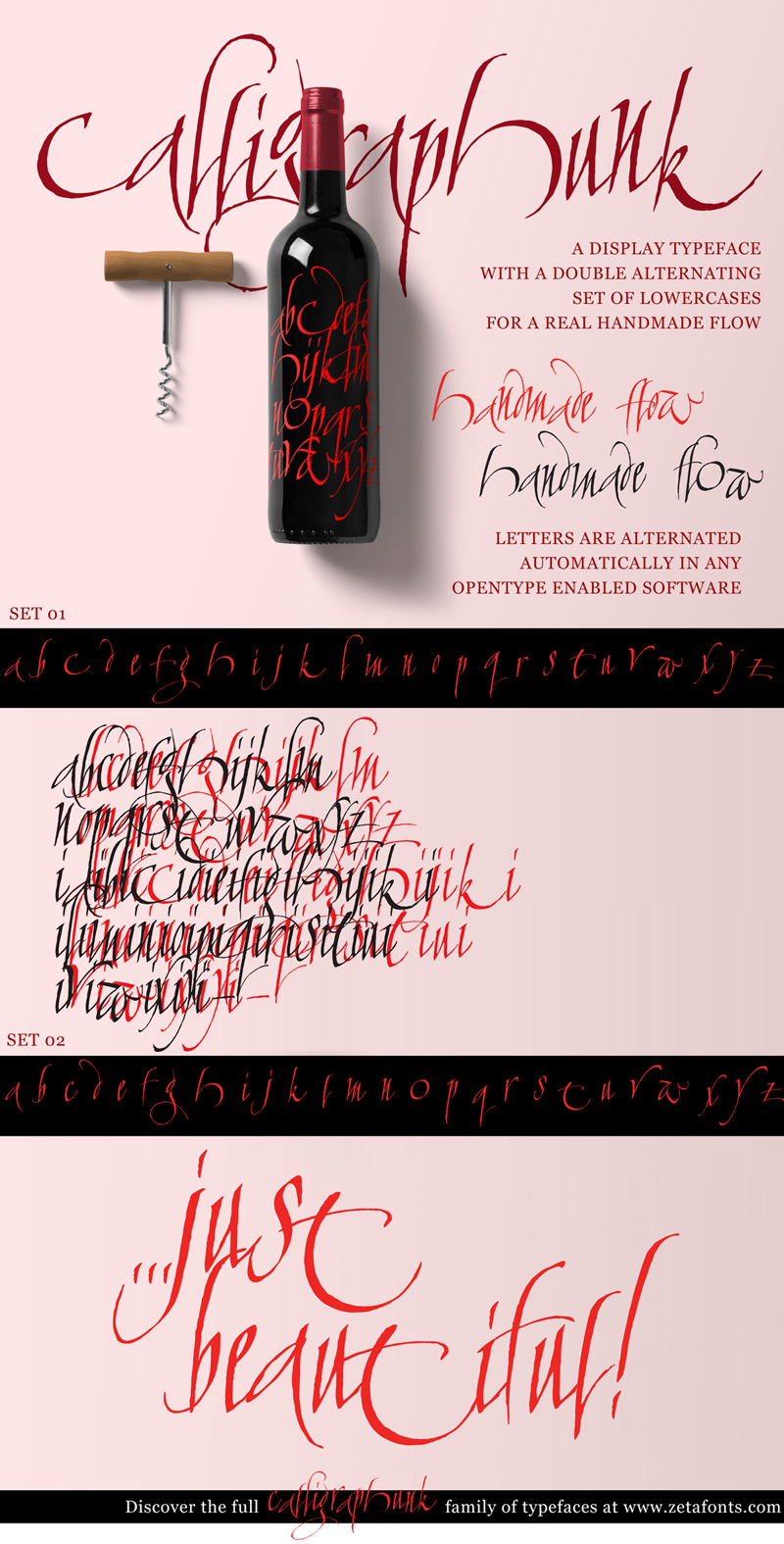
A Calligraphunk Font é uma novidade na categoria das fuentes de escrita cópica experimental. Inspirada no estiloso arte da caligrafia polirrímica, esta criação única apresenta duas conjuntos alternados de letras minúsculas para criar um tipo de texto que parece ter sido escrito à mão. A ideia é capturar o charme e a expressividade que somente a caligrafia pode oferecer em formato digital. Essa fonte foi criada pelo designer Hamilton, com uma proposta curiosa e vibrante. Sempre um passo além na busca por novas formas de expressão visual, a Calligraphunk é uma adição interessante à coleção de fuentes cópicas que já existem no mercado.